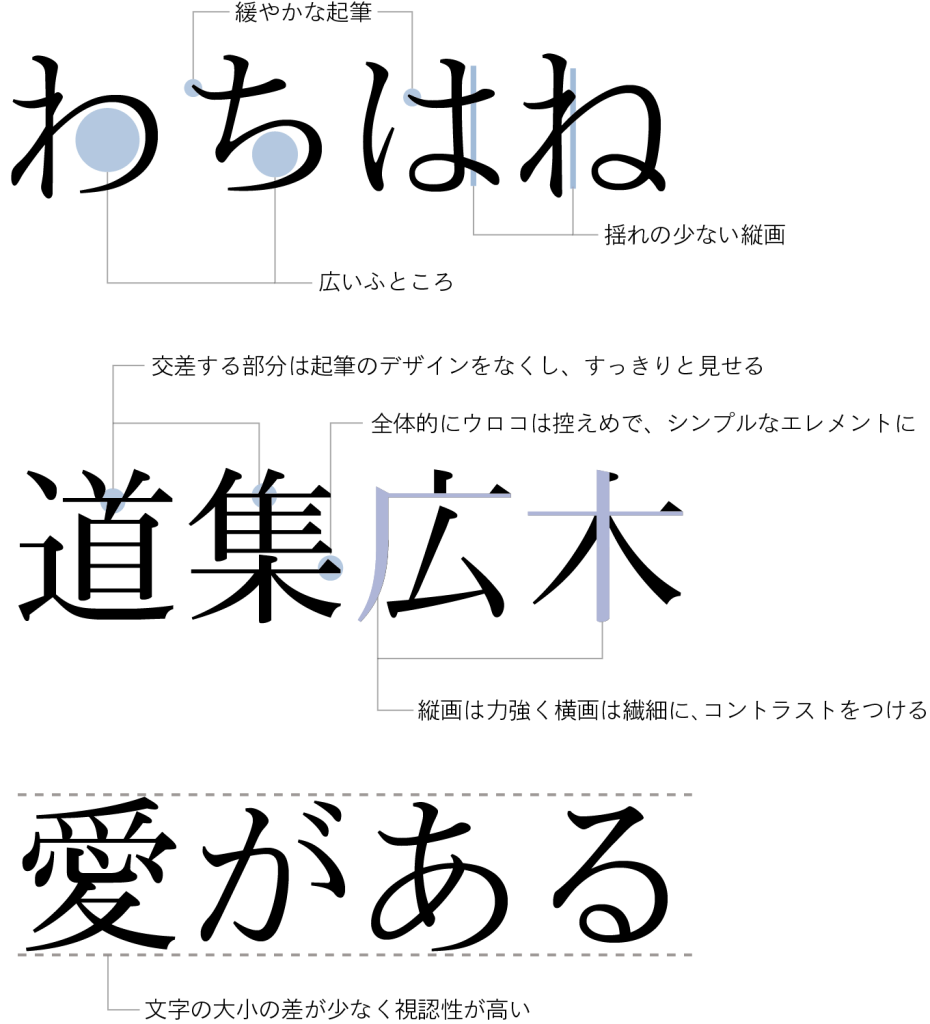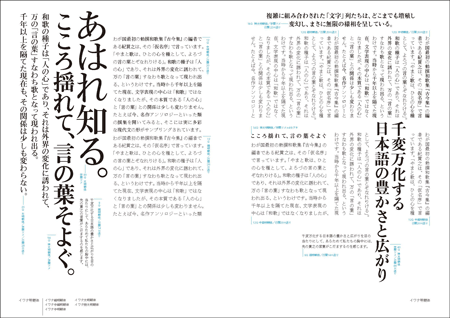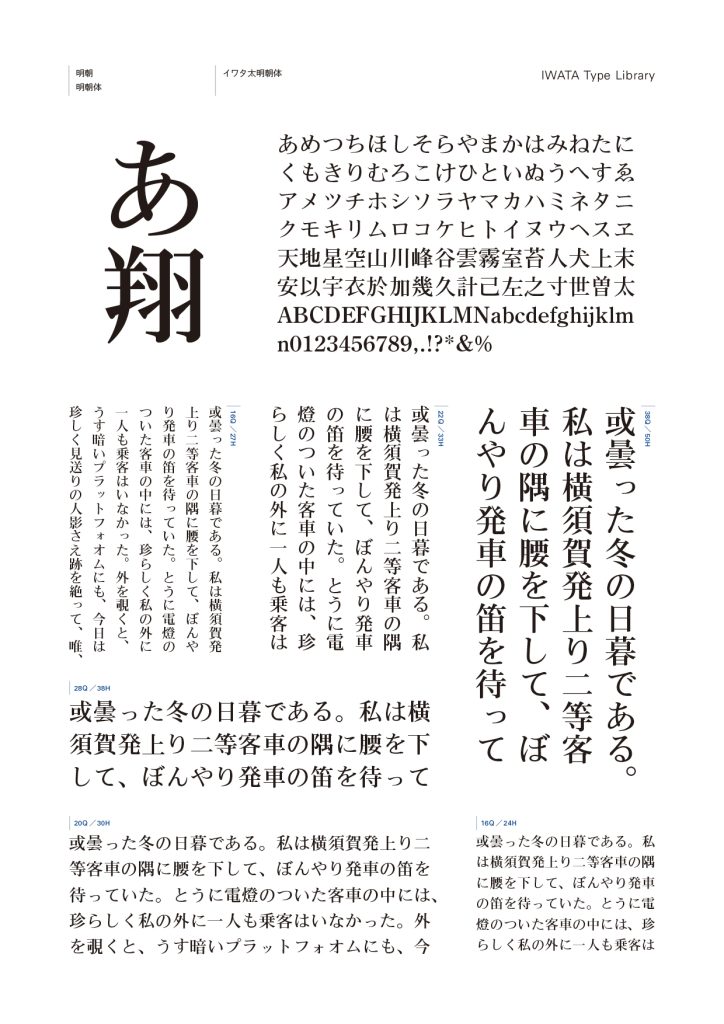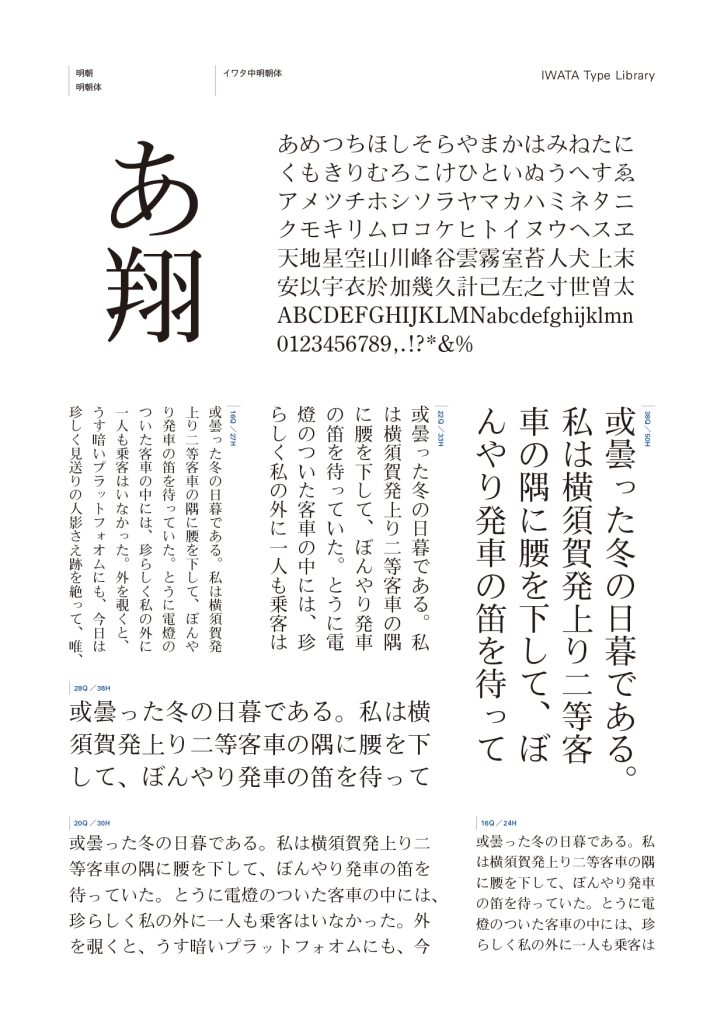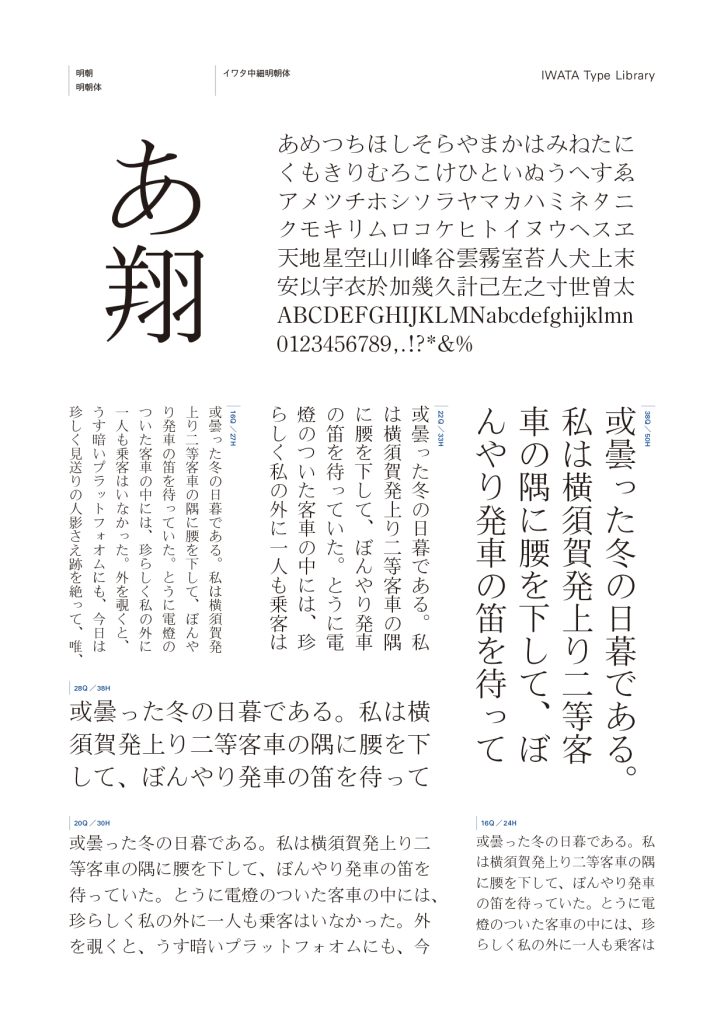
オーソドックスですっきりした印象の明朝体です。細いウェイトから見出し用の特太まで、幅広い文字組版に対応できます。繊細で上品な印象も落ち着いた安定感も与えられ、説明書や事務書類から出版物や広告まで、多くの場面で活用できます。
書体デザインのポイント
広いふところやシンプルなエレメントで、実直な趣があります。